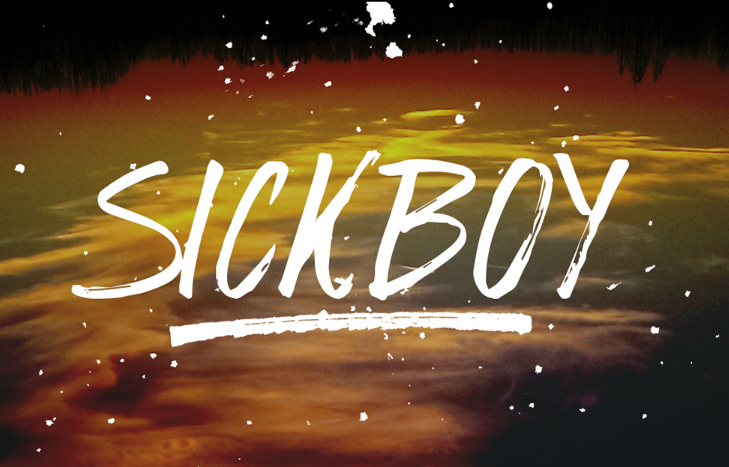
SickBoy Font é uma nova adição na coleção de nossas Brush Fonts, completamente gratuita para quem procura novos recursos gráficos. Esta fonte foi criada e compartilhada pelo designer Koen van der Bliek, conhecido por sua habilidade em criar tipos de letras com acabamento deslavado e dinâmico. Introduzida pela Rowo Typeface, SickBoy Font se destaca para ser usada em uma ampla gama de projetos gráficos. Da criação de design de envelope até a produção de cartões de visita ou panfletes, esta fonte pode ser aplicada com sucesso em vários campos. Suas formas fluidas e ativas permitem flexibilidade na expressão visual do seu trabalho. Seja você um designer criativo procurando por novos recursos para seus projetos, ou simplesmente alguém que adora uma tipografia única e vibrante, SickBoy Font certamente merece ser adicionada à sua coleção.